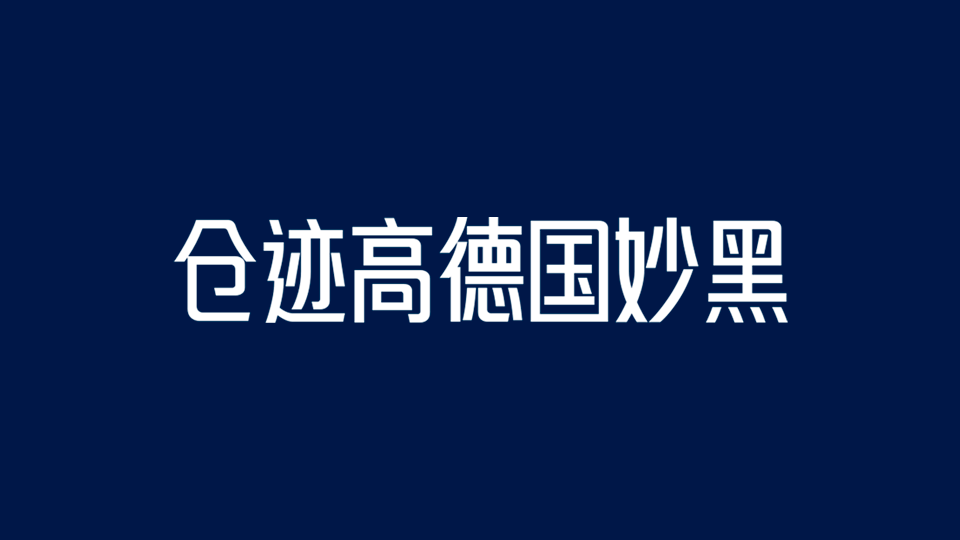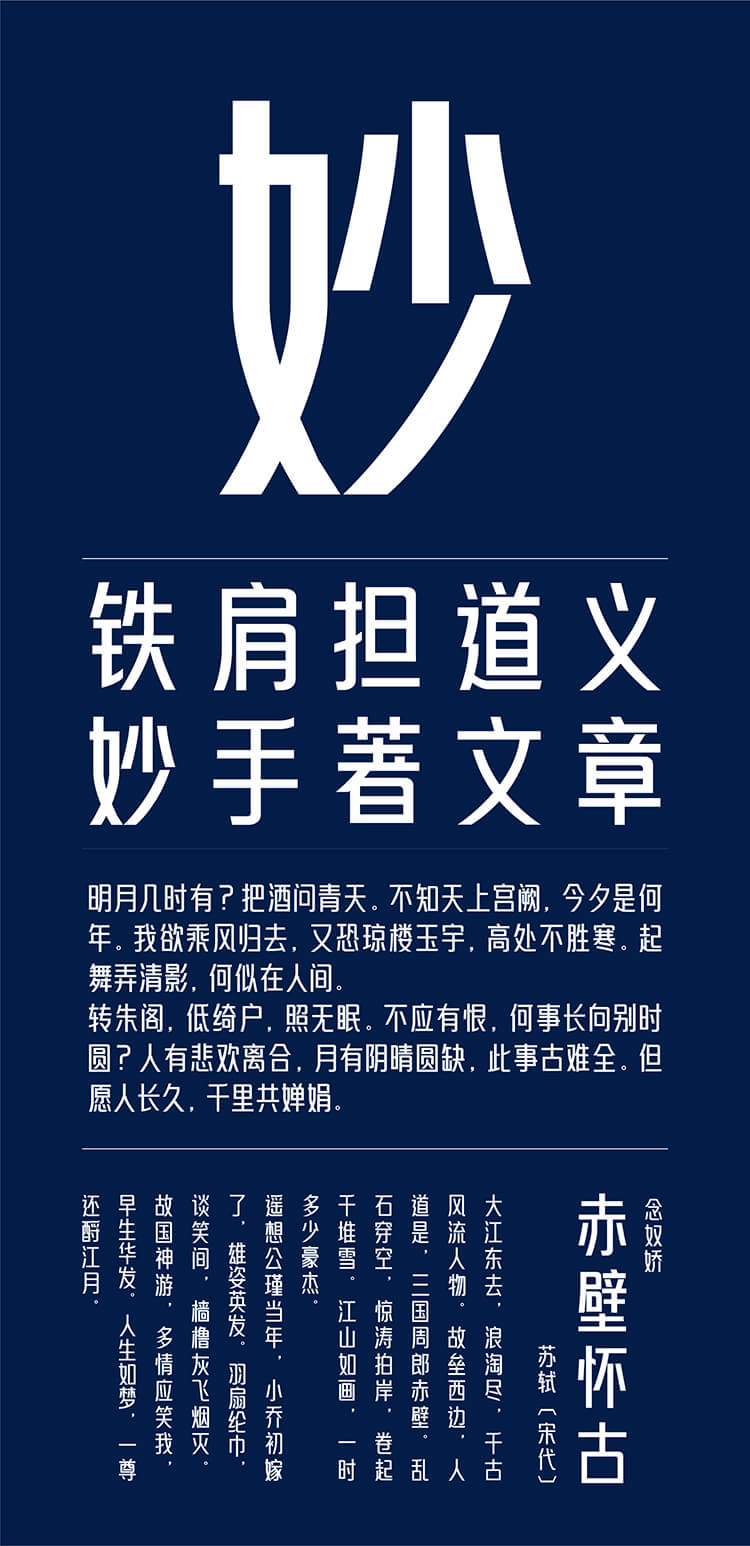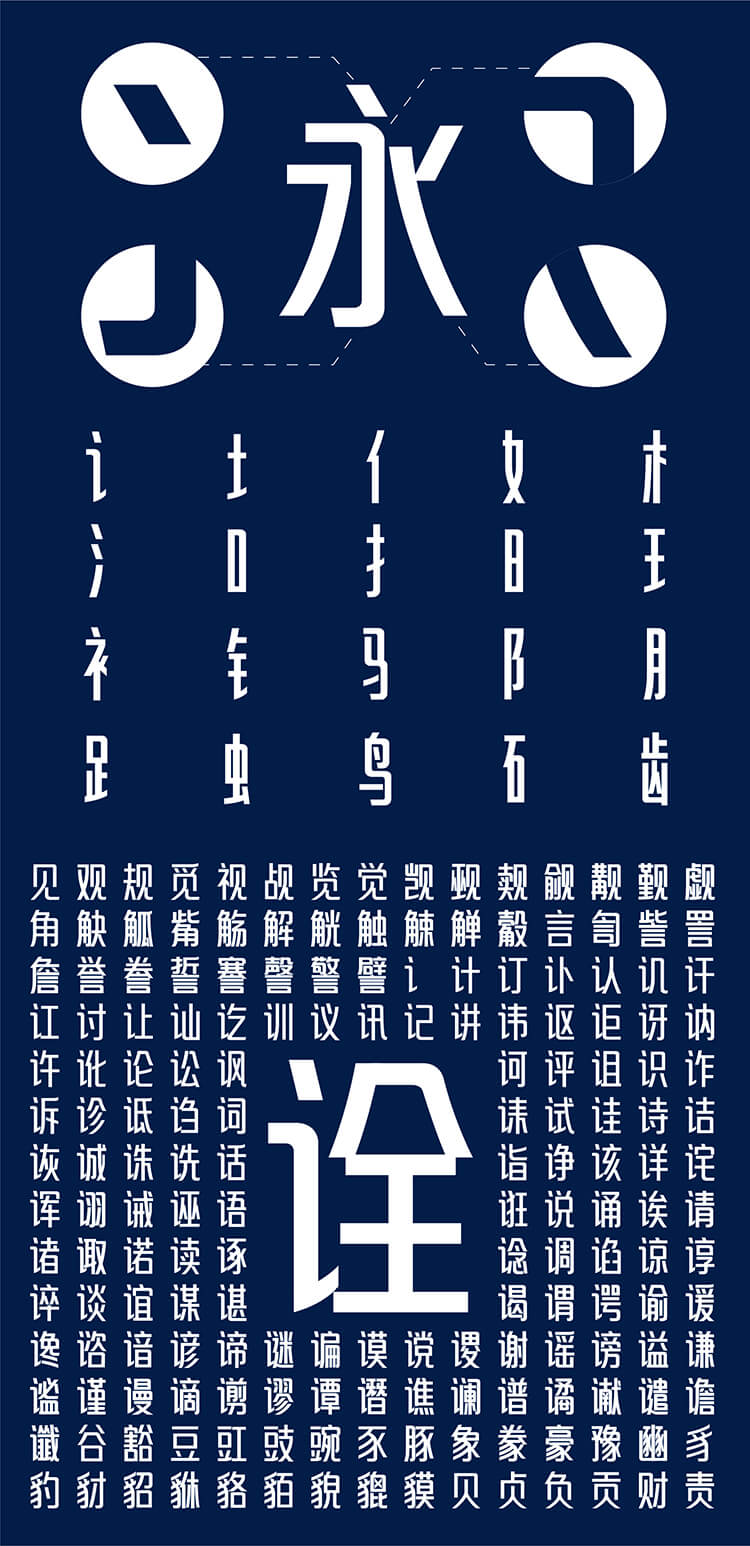
仓迹高德国妙黑高挑时尚,拉宽粗壮,做品牌设计必备,做广告标题良药,独特的高挑结构,使字体在商业创意设计中,可以更好的将字形与创意互相结合应用,能更好的为设计师服务,字体在各种行业众多场景都有出彩表现。
仓迹高德国妙黑字库字数:7155字,适用于品牌标志、招牌、包装、海报、影视综艺、广告、游戏、漫画等领域。